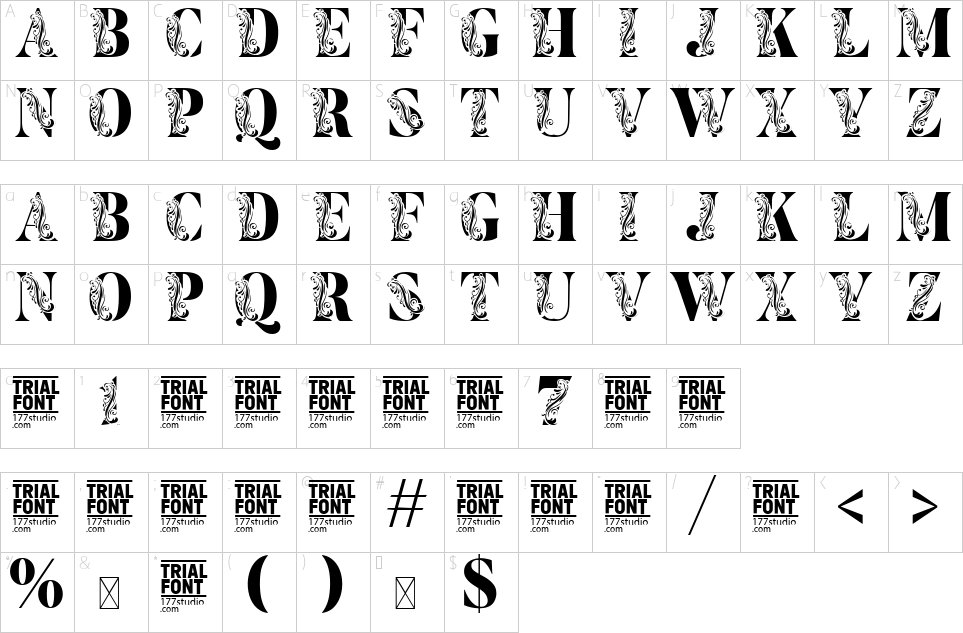
Flower Display Font – Download Grátis
Descubra a beleza inovadora do Flower Display Font com esta categoria de fontes gratuitas para Windows e Mac. Desenvolvida pela 177studio.com, esta fonte é perfeita para adicionar um toque único aos seus projetos digitais. Com traços elegantes e uma tipografia moderna, o Flower Display oferece diversas opções que vão desde letras florais delicadas até formas geométricas minimalistas. Desde o seu design cuidadoso, o Font Flower Display é perfeito para criar layouts memoráveis ou apenas adicionar um toque personalizado a sua próxima criação digital. Desfrute da versatilidade desta fonte e deixe suas ideias brilharem através de cada palavra. Não hesite em baixar esta fonte e experimentar o Flower Display. Você não encontrará nada igual.